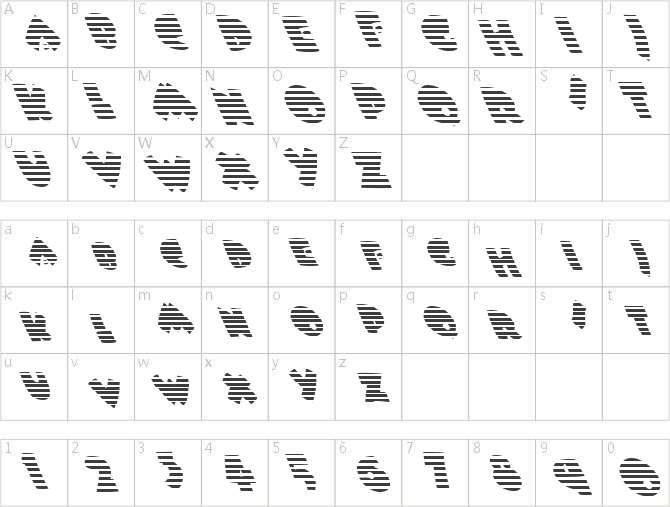
FZ JAZZY 9 STRIPED LEFTY
FZ JAZZY 9 STRIPED LEFTY介绍
FZ JAZZY 9 STRIPED LEFTY字体字库是一款让人赏心悦目、百看不厌的英文字体,适合各类广告和产品包装设计应用,字体大小0.08MB,格式为ttf字体,上传用户是82年的拉菲,作者/版权方为未知